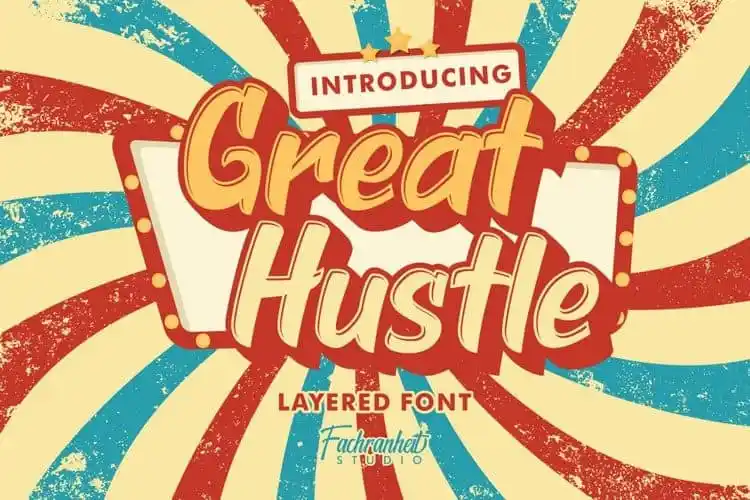
A fonte Great Hustle Display Font é uma escolha perfeita para qualquer projeto que exige um visual atraente e vibrante. Inspirada nos anúncios de banda vintage e na psicodelia dos anos 60, esta font se destaca por seu design poderoso e desafiador, criado pelo designer Fachranheit. Perfeito para headlines chamativas em revistas indie ou textos inovadores, Great Hustle é uma excelente opção para t-shirts, flyers e até mesmo para criar identidades de canais no YouTube. Seu característico estilo único o torna versátil, fazendo-o um recurso valioso não apenas para designers gráficos, mas também para quem procura uma font que brilhe em qualquer lugar. Com seu design robusto e vibrante, Great Hustle é certamente a fonte ideal para seus projetos futuros.